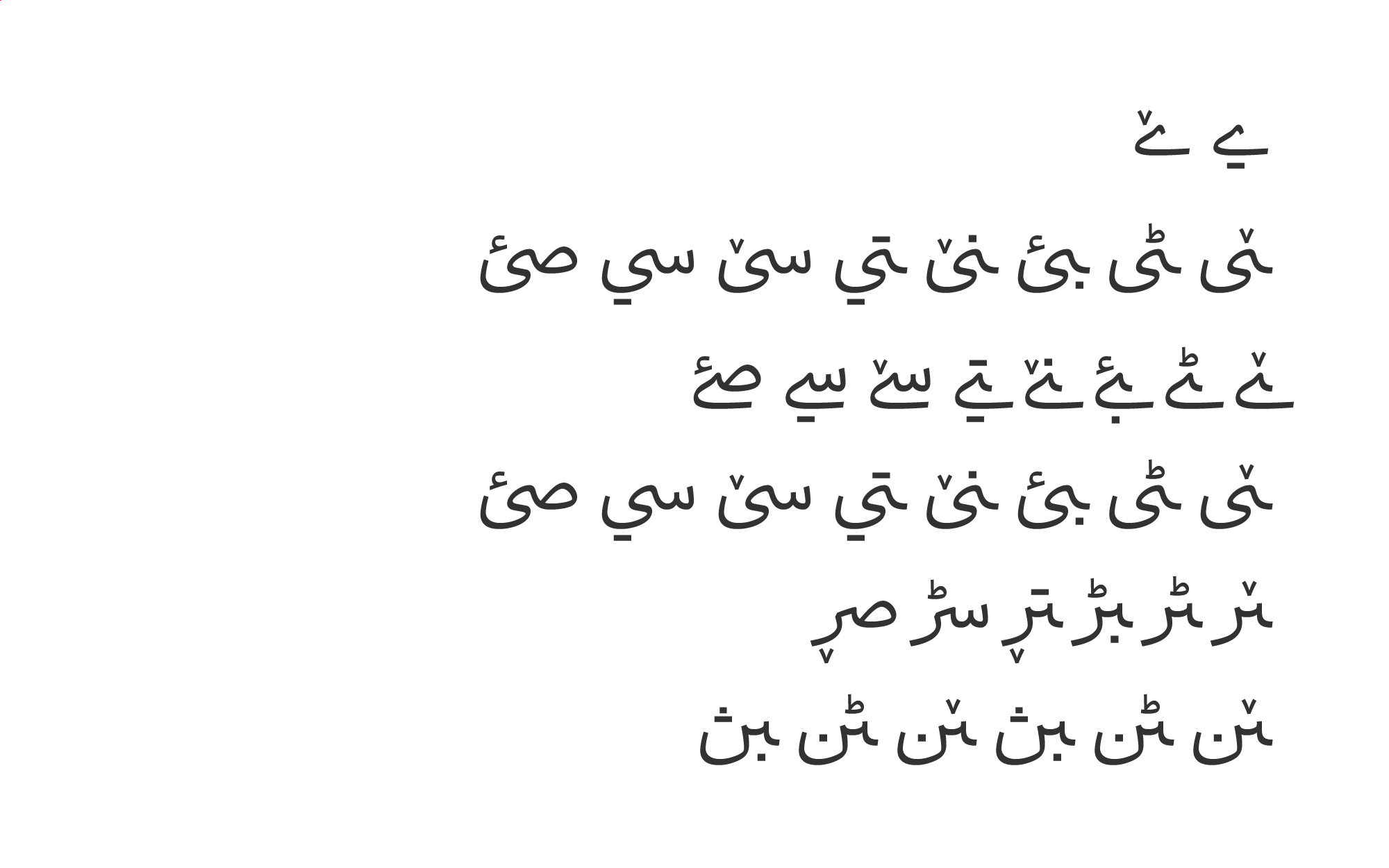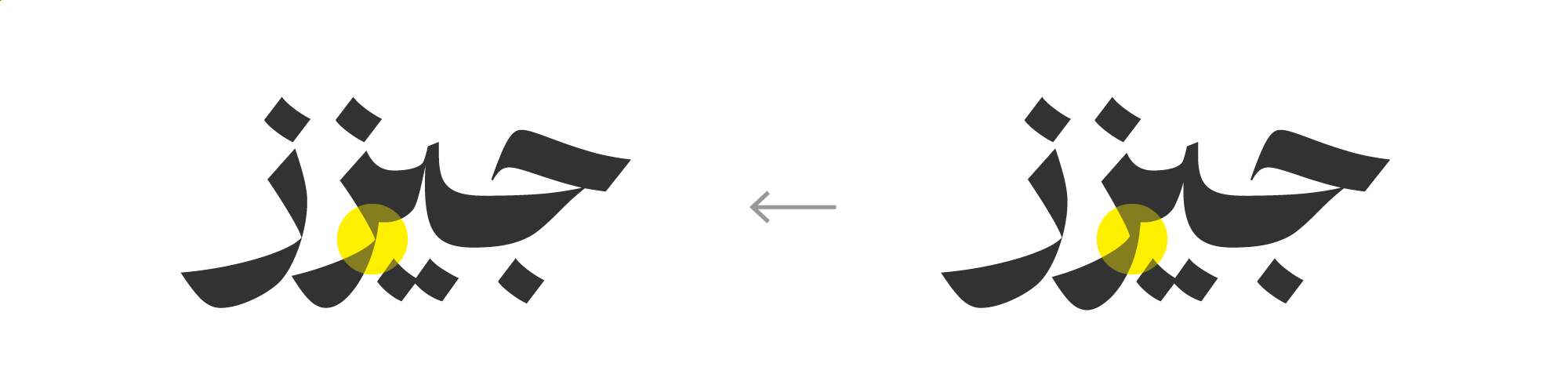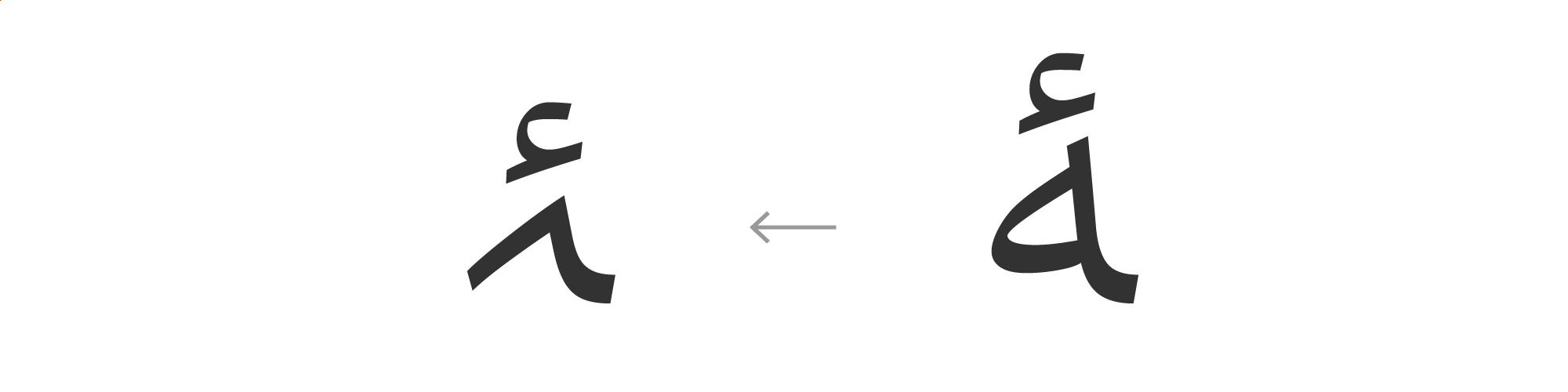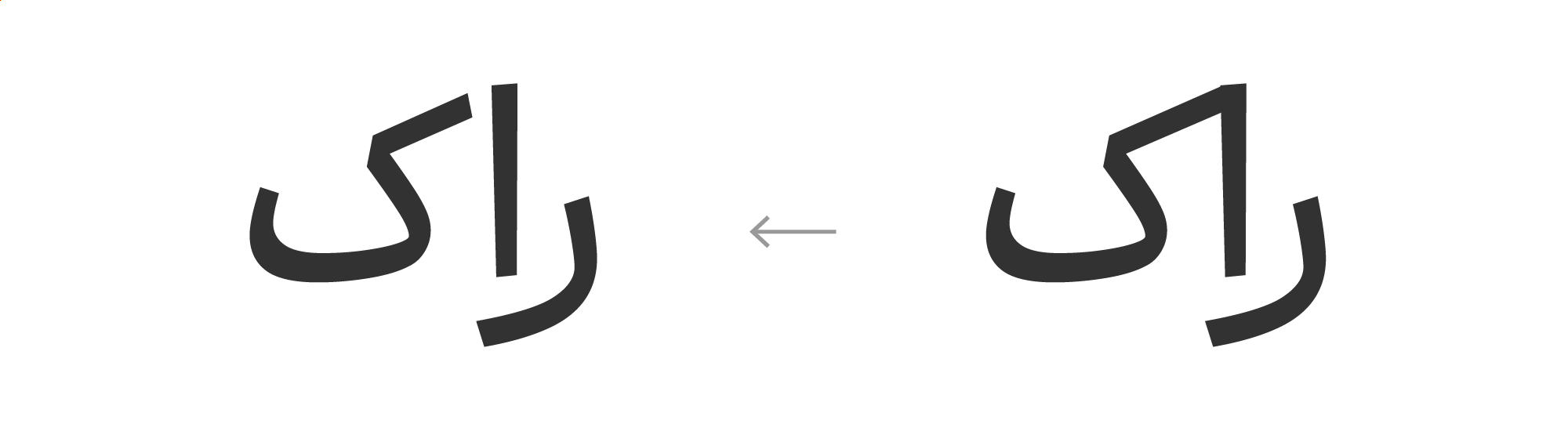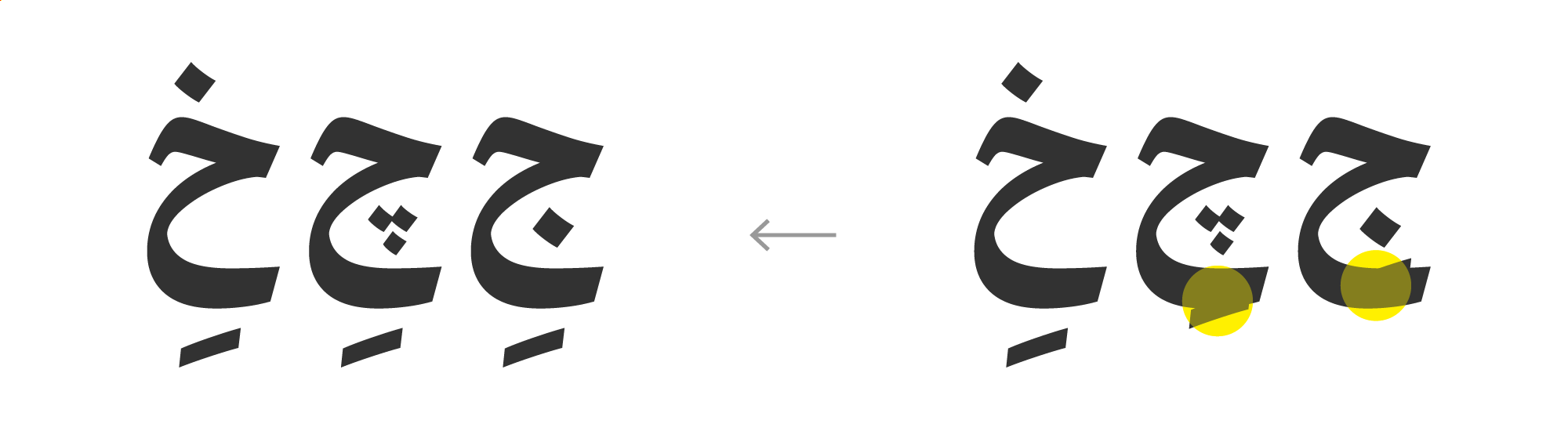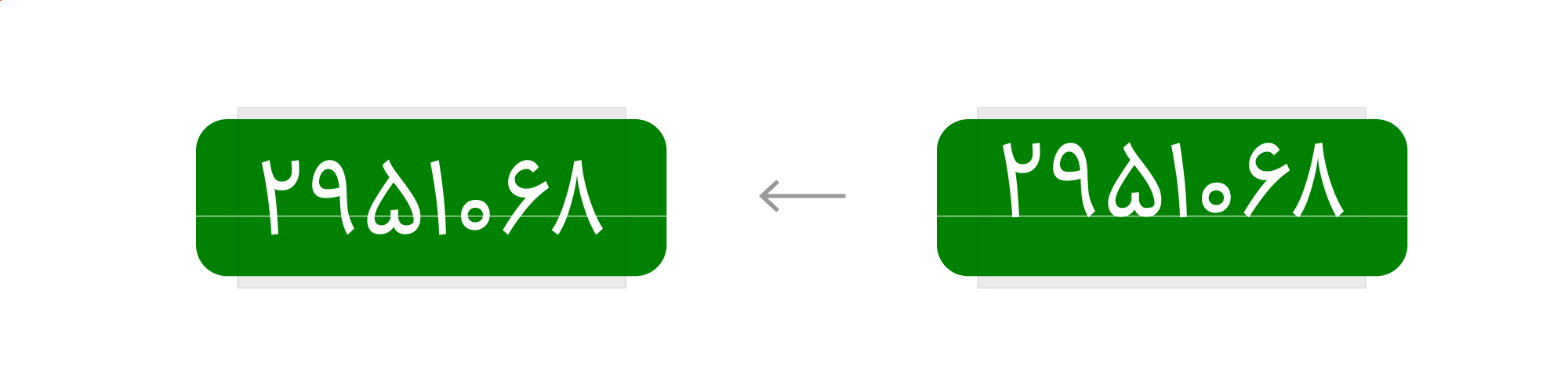
در نسخهی ۱٫۱ ابَر چه تغییراتی میبینیم؟
۱. لیگچرها، کشیدهها و حروف جایگزین برای زبانهای عربی، اردو و کوردی کامل شد.
۲. امکان تغییر تراز عمودی اعداد برای استفاده در UI فراهم شد.
۳. فرم «ر» کوتاه در لیگچرهای سبک High اصلاح شد.
۴. کاراکتر Heh Goal with Hamza above (U+06C2) مربوط به زبان اردو اصلاح شد.
۵. برخورد سرکش «ک» با الفِ بعد از «ر» اصلاح شد.
۶. جای اعراب پایین «ج» و «چ» اصلاح شد.